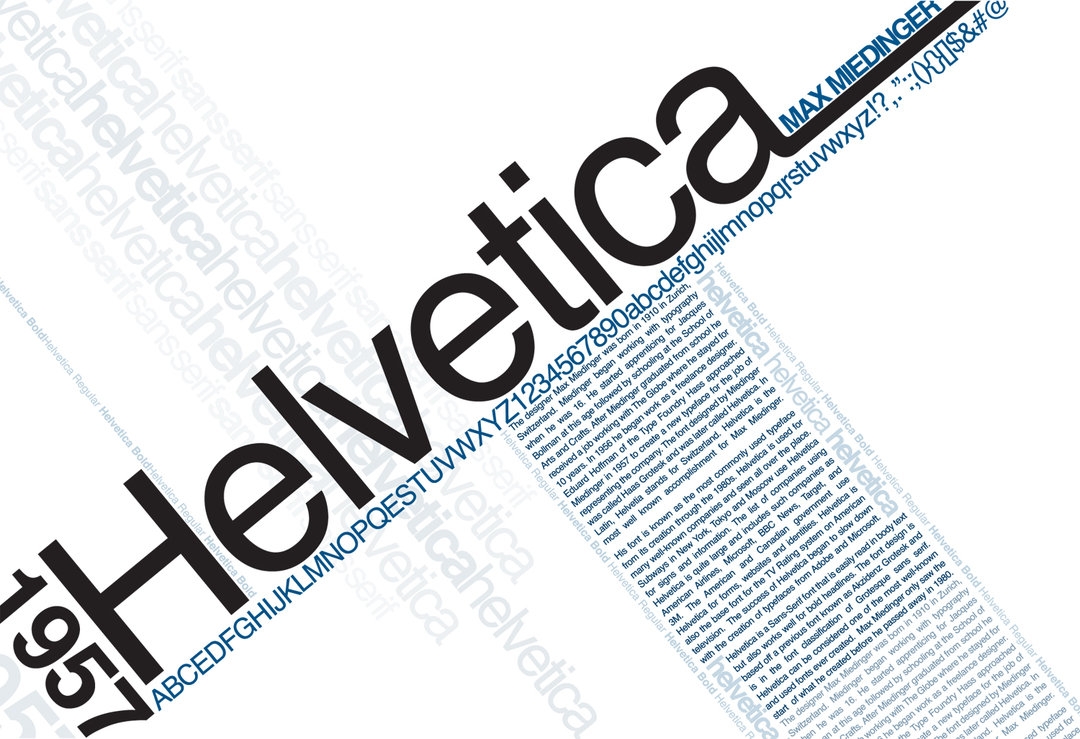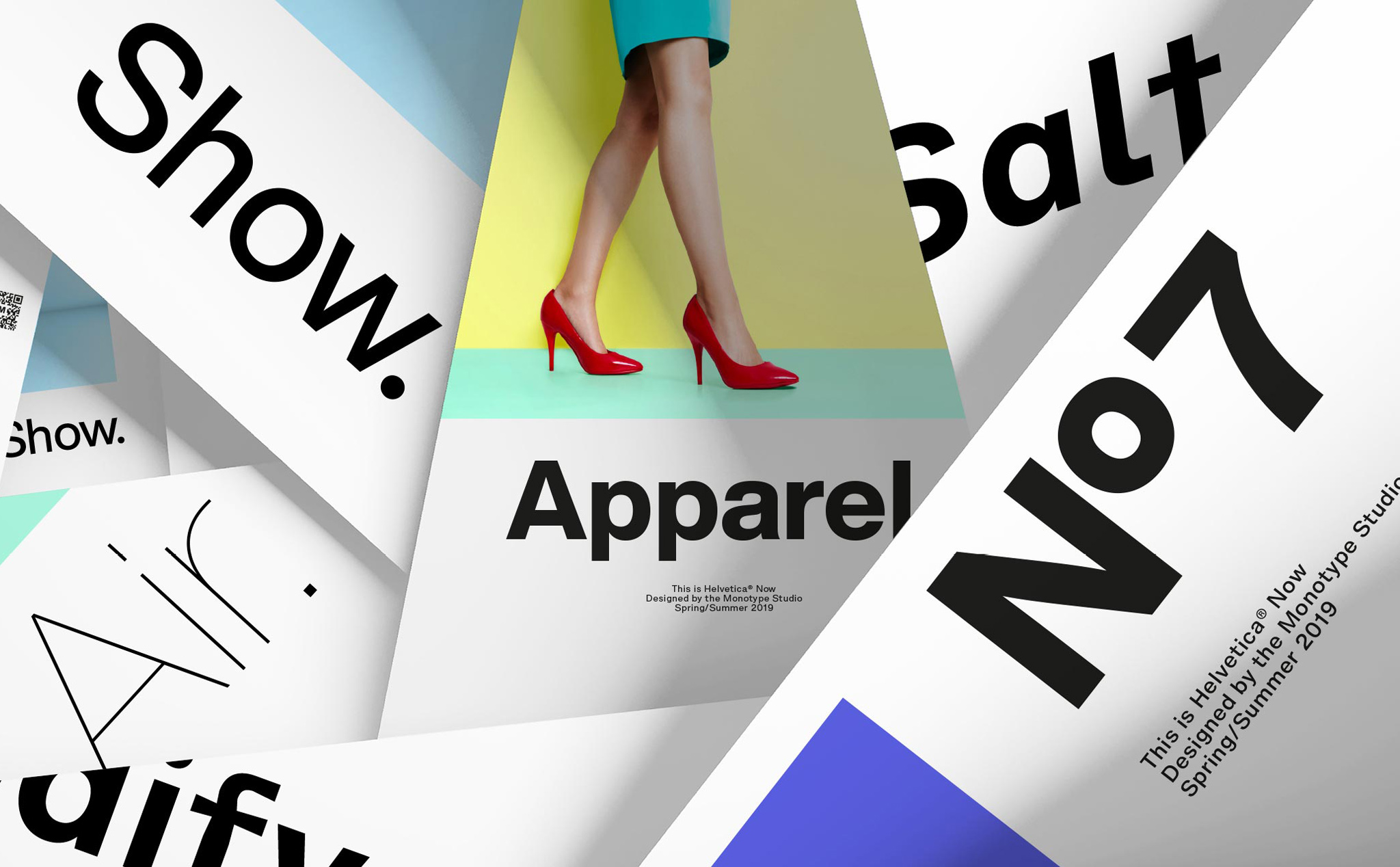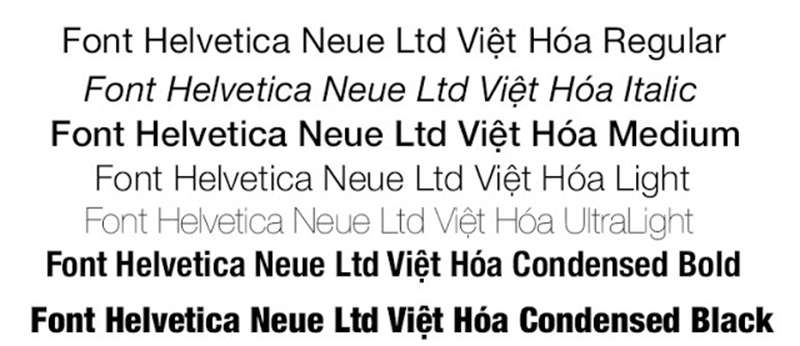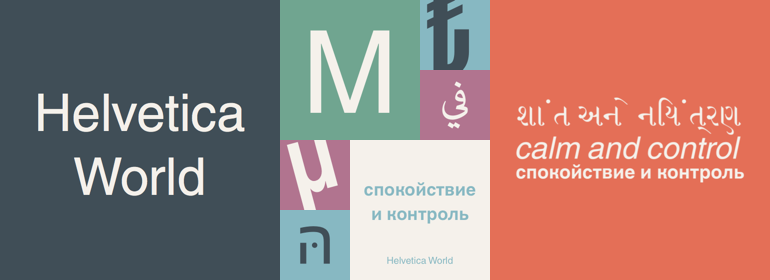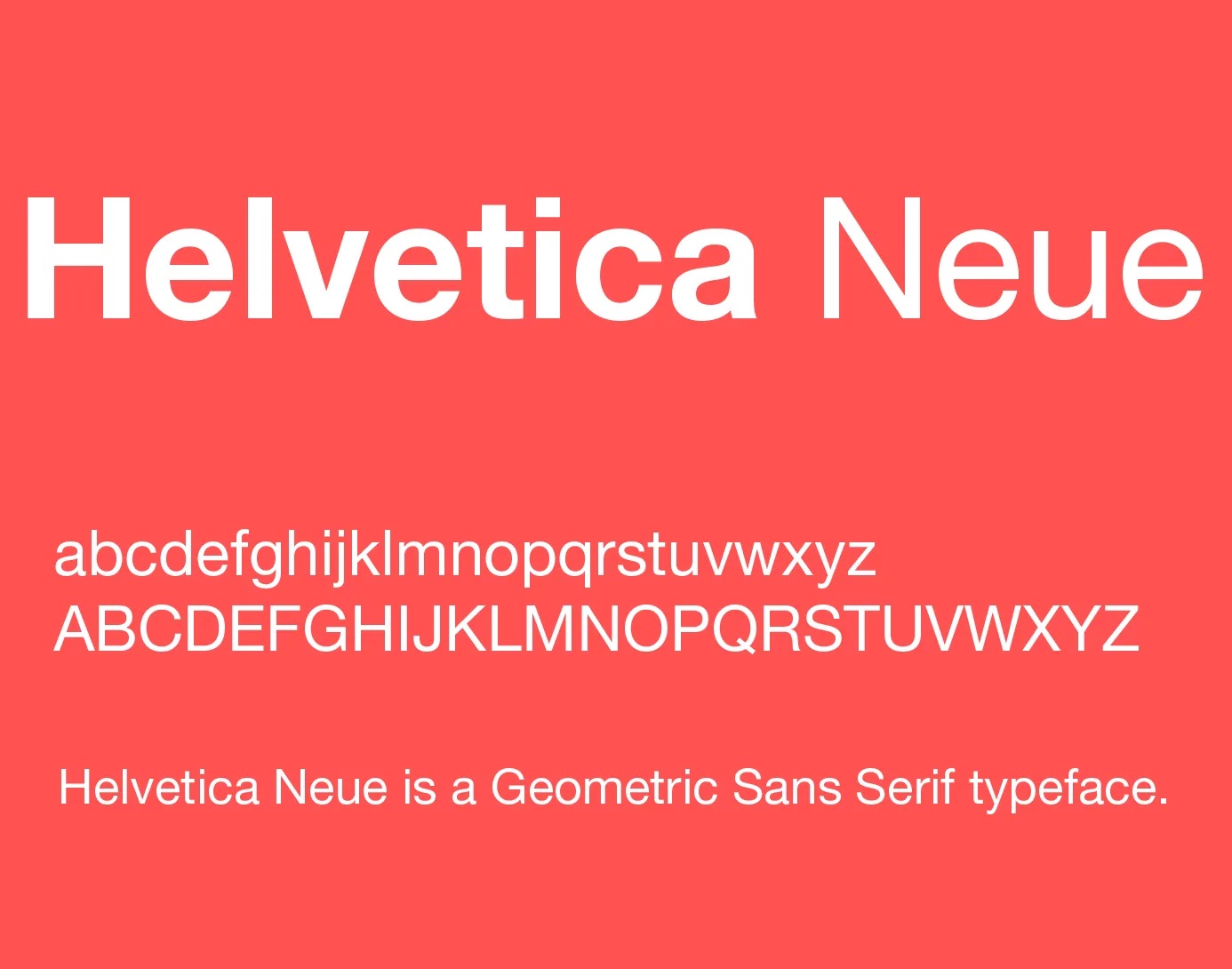
Helvetica đã từ lâu trở thành một trong những bộ font chữ được sử dụng nhiều nhất và nổi tiếng nhất trên thế giới. Đặc điểm nổi bật của nó là vô cùng cơ bản và dễ dàng sử dụng trong nhiều trường hợp khác nhau. Cho nên nó trở thành bộ font không thể thiếu đối với những người thiết kế hay đơn giản chỉ là làm việc văn phòng.
Bằng chứng là hiện giờ rất nhiều trang web trên thế giới đang dùng bộ font chữ này. Một điển hình của font chữ Helvetica đã đi vào lịch sử là trở thành bộ chữ chính thức. Trong hệ thống tàu điện ngầm ở thành phố New York. Trong bài viết này chúng ta sẽ cùng nhau tìm hiểu kỹ hơn về bộ font thú vị này nhé
Font HELVETICA là gì?
Font Helvetica là một bộ Font chữ dạng sans-serif không chân có thể nói. Là được sử dụng nhiều nhất hiện nay tại đa số các quốc gia trên thế giới trong đó có Việt Nam. Mặc dù có nguồn gốc từ nước ngoài nhưng vì nó quá thú vị cho nên Font Helvetica được nhiều người Việt Nam hỗ trợ Việt hóa. Lại bộ Font Helvetica để cho nó trở nên phổ biến, nhiều người có thể sử dụng được hơn.
Năm 1957 dựa theo những phác thảo thiết kế trước đó của một người tên là Eduard Hoffmann. Một nhà thiết kế người Thụy Sĩ tên là Max Miedinger đã sáng tạo ra Font Helvetica.
Tuy nhiên ban đầu người ta chưa gọi nó là Font chữ Helvetica. Mà nó được gọi bởi một cái tên khác là Neue Haas Grotesk (New Haas Grotesque) và được Linotype cấp phép sử dụng.
Cái tên font Helvetica là được đặt vào năm 1960 và được giữ nguyên cho đến tận bây giờ. Khi đã trở thành một font chữ nổi tiếng và thông dụng nhất trên thế giới.
Ngay từ khi ra đời với đặc tính trung tính đa phong cách nhưng lại rất rõ ràng của mình font Helvetica. Đã được sử dụng trên nhiều loại biển báo khác nhau, và cứ thế nó tạo nên một xu hướng, một phong cách trong thế giới font style ngày đó.
Cho đến cuối năm 2007, để kỷ niệm tròn 50 năm font chữ này ra đời thì một cuộc triển lãm. Với tên gọi “50 years of Helvetica” đã được tổ chức tại thành phố New York. Trong cuộc triển lãm này cũng đã trình chiếu một bộ phim tư liệu đặc biệt của đạo diễn Gary Hustwit. Nói về Font chữ Helvetica, đánh dấu mốc 50 năm font chữ này ra đời.
Không dừng lại ở đó, sự nổi tiếng của font chữ vẫn tiếp diễn đến năm 2011. Đã có 1 cuộc triển lãm xoanh quanh những vấn đề về font chữ này được tổ chức với tên gọi “Helvetica. A new Typeface? thu hút đông đảo sự quan tâm của giới thiết kế nhất là sử dụng thiết kế để in túi giấy cho các công ty
Điểm nổi bật của font HELVETICA Việt hóa
Nếu không phải là dân thiết kế chuyên nghiệp và thường xuyên làm việc với các font chữ. Thì hầu hết các font chữ đều nhìn khá giống nhau và khó phân biệt. Nhưng nếu như bạn đã từng làm việc với rất nhiều font chữ thì có thể phân biệt rõ ràng. Những điểm khác biệt chỉ có ở font Helvetica.
Chẳng hạn như chữ G sẽ có nét thẳng ở dưới chân. Hay chữ A sẽ có nét cong và tròn ở phần chân và bụng của chữ,… Tùy theo từng trường hợp mà font chữ Helvetica được sử dụng với nhiều mục đích khác nhau. Chính vì sự thú vị và đa dạng này mà font Helvetica được sử dụng trong nhiều bối cảnh khác nhau.
Ví dụ thường thấy là người ta thường sử dụng font Helvetica để làm logo từ Typeface. Ngoài ra cũng có thể sử dụng font chữ Helvetica để làm phần tiêu đề hay nội dung. Cho nhiều loại tác phẩm khác nhau.
Tính đến thời điểm hiện tại, font Helvetica có hơn 68 Typeface khác nhau. Được sử dụng phù hợp với từng ngữ cảnh tương ứng mà font chữ Helvetica. Đã trở thành một trong những font chữ Typeface có số lượng biến thể đông đảo nhất trên Thế giới.
Một số font HELVETICA Full Việt hóa
Mặc dù có nguồn gốc nước ngoài nhưng với sự tiện lợi và hiệu quả nên bộ font này đã được Việt hóa để có thể sử dụng gõ văn bản tiếng Việt. Mặc dù có khá nhiều phiên bản khác nhau nhưng bài viết xin được chia sẻ một số font chữ Helvetica Việt hóa dưới đây:
Font chữ HELVETICA WORLD Việt hóa
Font chữ HELVETICA NEUE Việt hóa